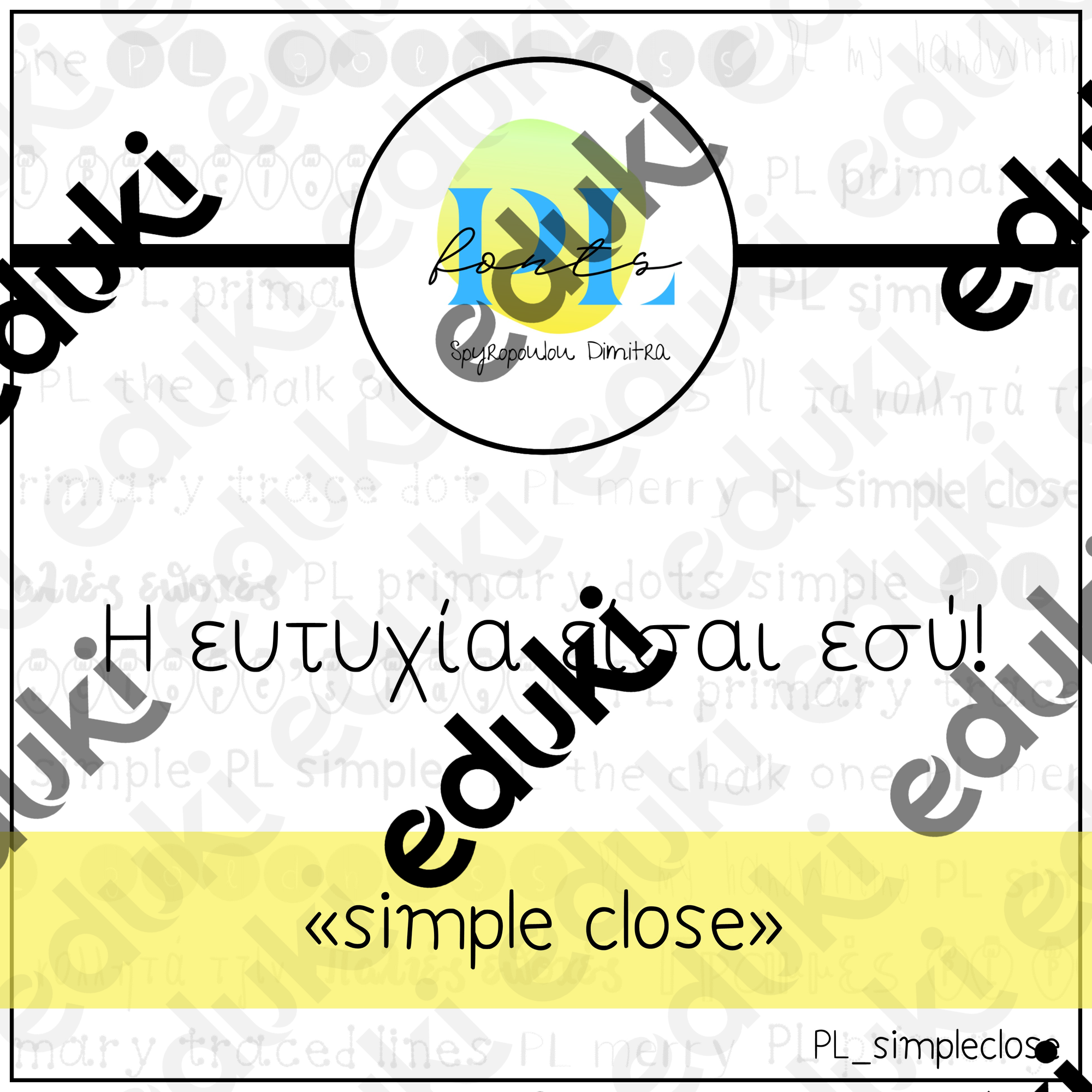
Αυτή η γραμματοσειρά ονομάζεται "simple close" (η κοντινή κι απλή) και αποτελεί γραμματοσειρά κειμένου (text font). Είναι γράμματα που έχουν κανονική ένταση και είναι υπέροχη για εκπαιδευτικούς λόγους, καθότι τα γράμματα γράφονται όπως συνηθίζουν να τα μαθαίνουν τα παιδιά στο σχολείο.
Είναι ίδια με την "simple", αλλά τα γράμματά της βρίσκονται πιο κοντά το ένα στο άλλο.
Η γραμματοσειρά περιλαμβάνει ελληνικούς χαρακτήρες καθώς και αγγλικούς, αριθμούς, μαθηματικά σύμβολα και σημεία στίξης.
This font is called "simple close" and it's a text font. It's like the font named "simple", but the letters are much closer.
This font includes Greek characters as well as English ones, numbers, mathematical symbols, and punctuation marks.